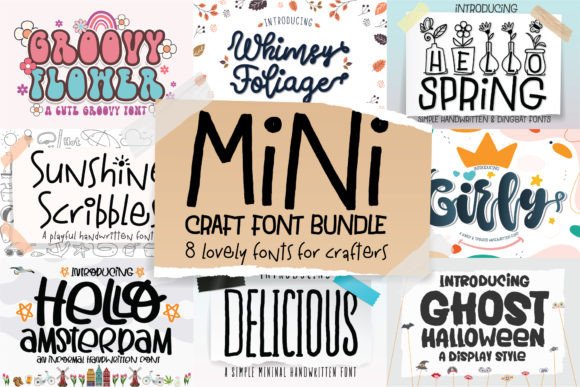
Mini Craft Bundle
Mini Craft Bundle์™€ ๊ฐ™์€ ๊ณ ํ’ˆ์งˆ ์ž์‚ฐ์„ ์ฐพ๊ณ  ์žˆ๋‹ค๋ฉด ์ด ํ”„๋ฆฌ๋ฏธ์—„ ํŒจํ‚ค์ง€๋Š” ์ฐฝ์˜์ ์ธ ํ”„๋กœ์ ํŠธ๋ฅผ ์œ„ํ•œ ํ™˜์ƒ์ ์ธ ์„ ํƒ์ž…๋‹ˆ๋‹ค.
์ •๋ฐ€ํ•˜๊ฒŒ ์ œ์ž‘๋œ Mini Craft Bundle๋Š” ๊น”๋”ํ•œ ๋ฒกํ„ฐ, ๋ถ€๋“œ๋Ÿฌ์šด ํƒ€์ดํฌ๊ทธ๋ž˜ํ”ผ ๋ฐ ์•ˆ์‹ฌํ•  ์ˆ˜ ์žˆ๋Š” ์ƒ์—…์šฉ ๋ผ์ด์„ ์Šค๋ฅผ ์ œ๊ณตํ•ฉ๋‹ˆ๋‹ค.
POD(์ฃผ๋ฌธํ˜• ์ธ์‡„) ์ œํ’ˆ, ๊ฒฐํ˜ผ์‹ ์ดˆ๋Œ€์žฅ ๋˜๋Š” ์†Œ์…œ ๋ฏธ๋””์–ด ๊ทธ๋ž˜ํ”ฝ์„ ๋งŒ๋“ค ๋•Œ Mini Craft Bundle๋Š” ์ด์ƒ์ ์ธ ์„ ํƒ์ž…๋‹ˆ๋‹ค.